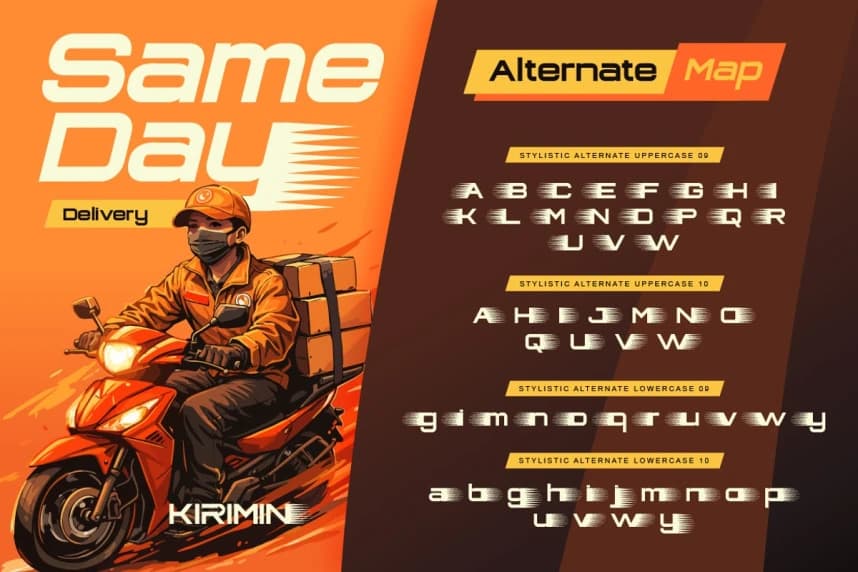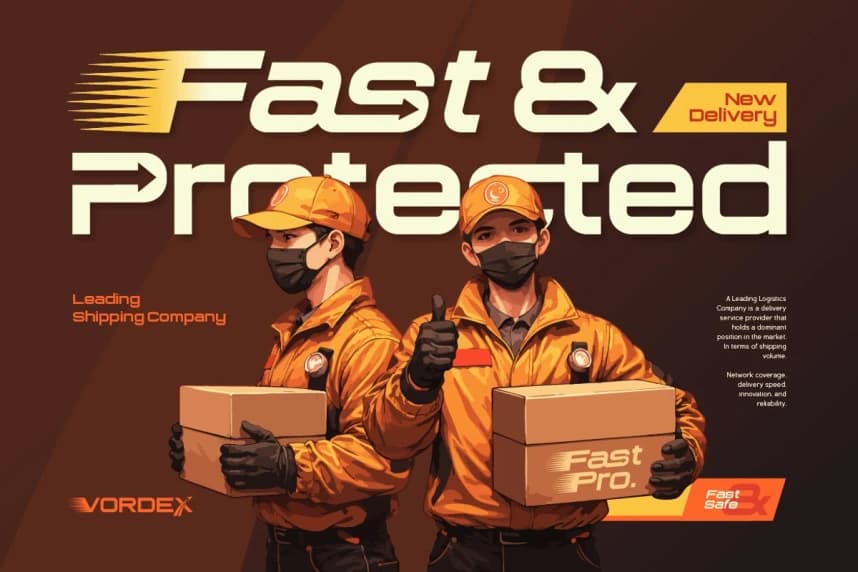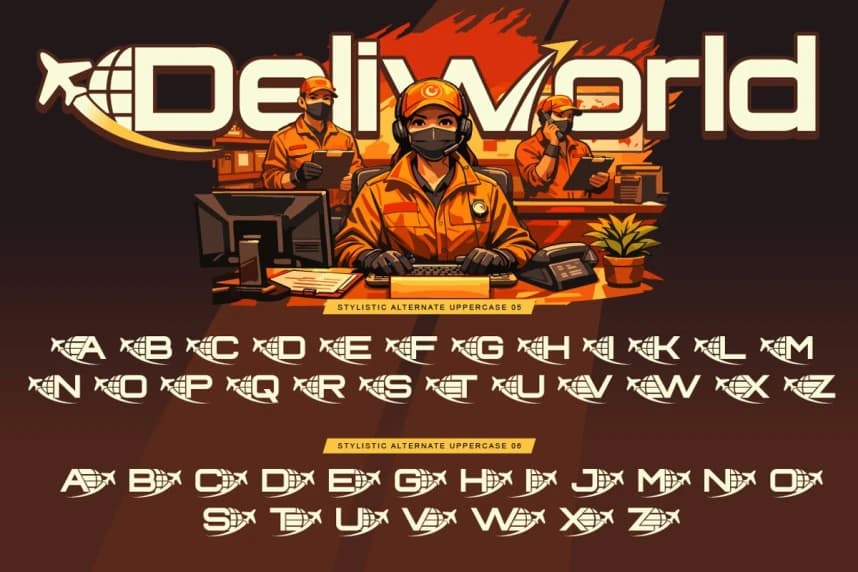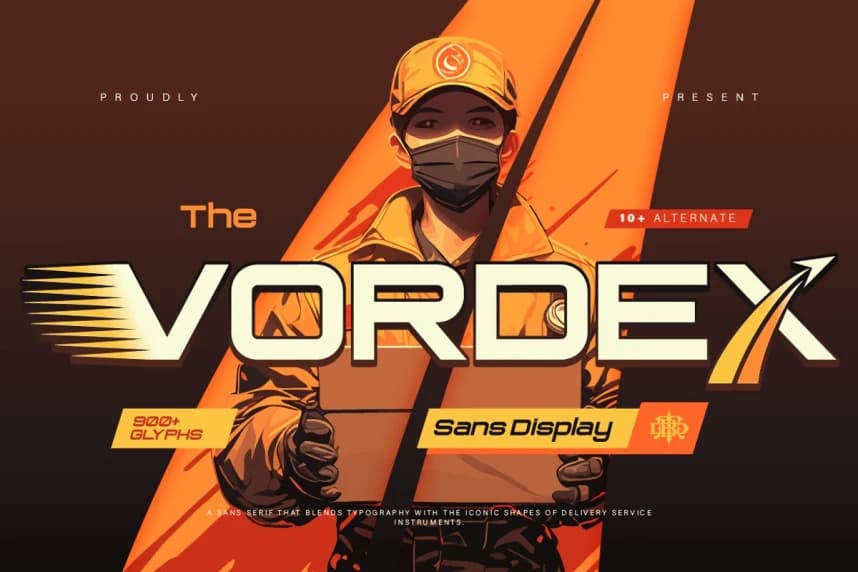
Vordex Font
Vordex Font, lojistiğin ve teslimatın hızlı tempolu dünyasından ilham alan cesur ve modern bir sans gösterim yazı tipidir. Güçlü geometrik şekiller ve dinamik kesimler ile tasarlanmıştır; bu yazı tipi tasarımlarınıza hız, verimlilik ve güvenilirlik hissi katıyor.
Vordex Font, lojistik ve dağıtımın hızlı tempolu dünyasından ilham alan cesur ve modern bir sans display yazı tipidir. Güçlü geometrik şekiller ve dinamik kesimlerle tasarlanmıştır; bu yazı tipi tasarımlarınıza hız hissi, verimlilik ve güvenilirlik katar.